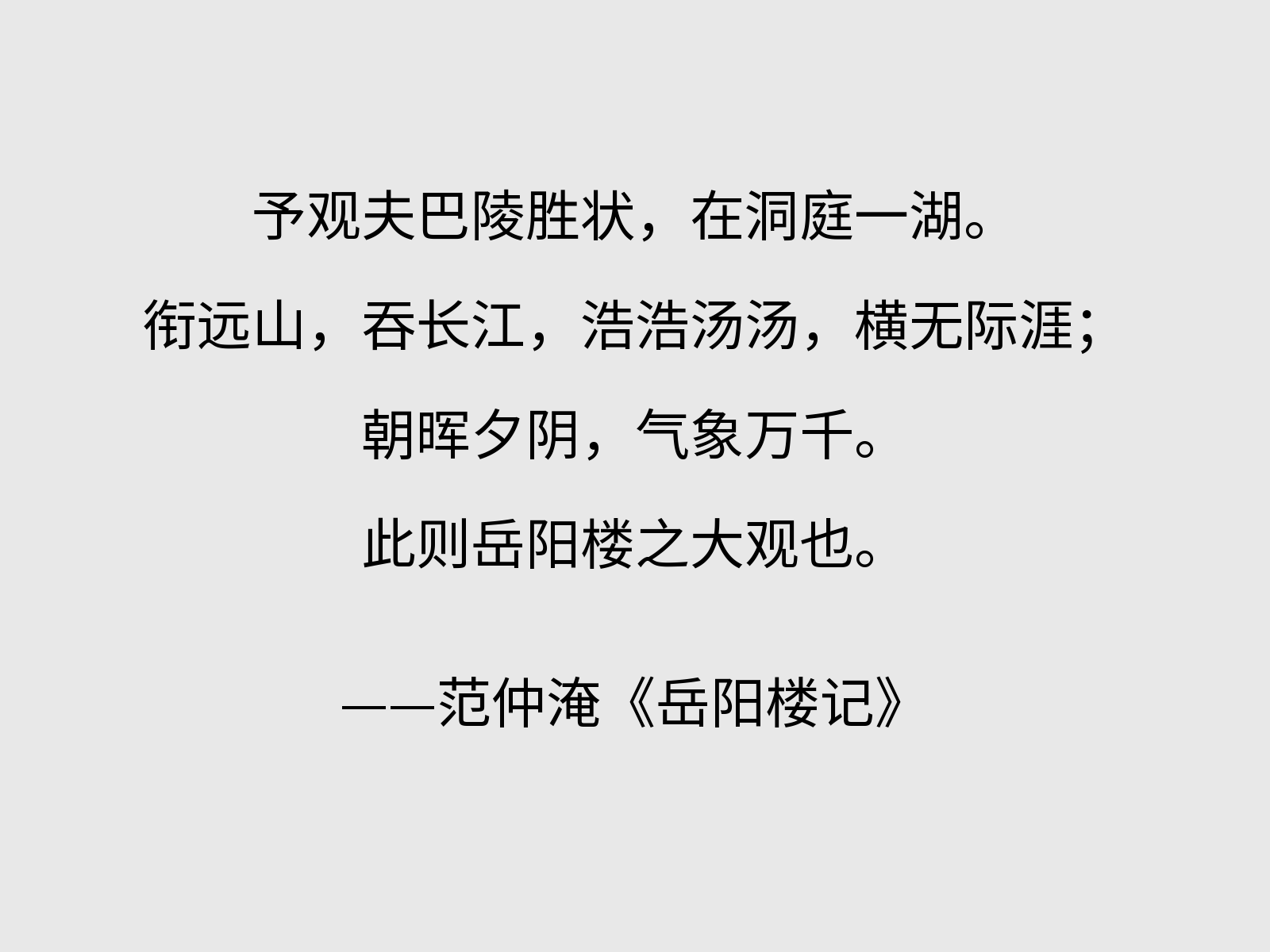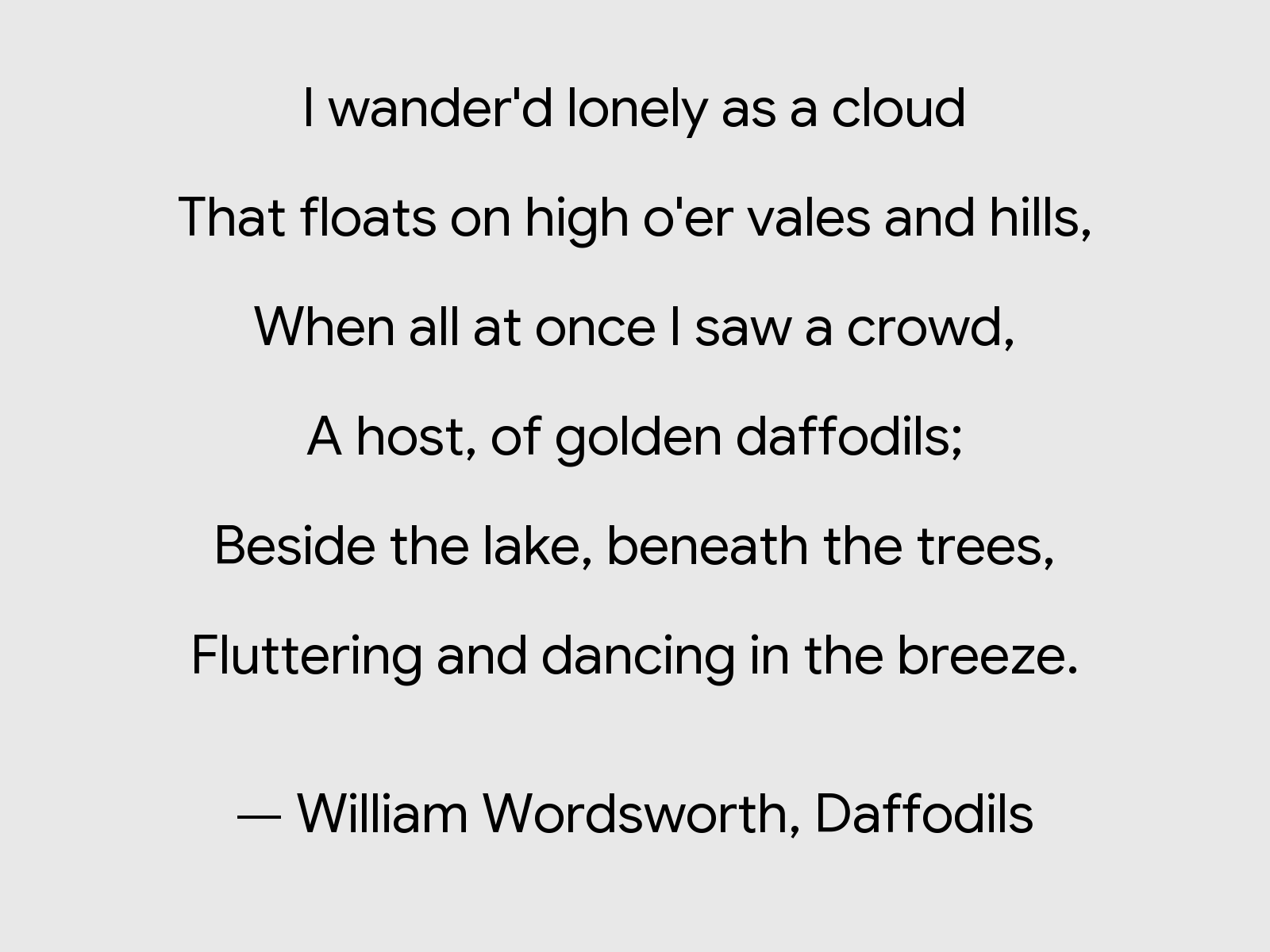
圆构黑体,基于 Google Sans、思源黑体和昭源黑体,商用免费的多文种混排字体。
制作动机
2025 年 11 月,谷歌开源了 Google Sans,该字体支持了极为可观的 19 种文字,同时也有不错的质量。为方便使用,缝合了思源黑体。
本字体名称由谷歌 Gemini 所取(英文名稍作修改),Gemini 称其为“直观体现几何(Geometry)与思源(Source)的重构”。
提供圆构黑体 Alt,采用等宽数字、全角引号和单层 a。
圆构黑体: 使用 Google Sans 原版样式圆构黑体 Alt: 采用等宽数字、全角引号和单层a
CHS: 中国内地字形CHT: 昭源现代笔形JPN: 日本字形